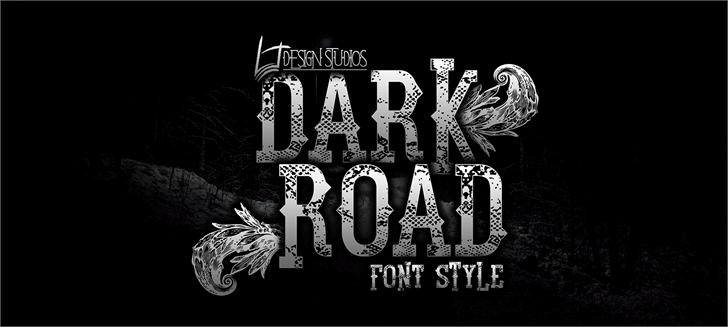
Dark Road Font – Fonte Grátis
Dark Road Font
A fonte ‘Dark Road Font’ é perfeita para criar design decorativos que se destacam na sua página web ou material impresso. Feita pelo designer Hamilton, essa fonte oferece linhas finas e elegantes com um toque sombrio que a torna ideal para ambientes criativos e interessantes. Com o uso desse recurso gráfico único, você pode adicionar um tom de profundidade única aos seus designs digitais. A ‘Dark Road Font’ é perfeita para criação de logotipos memoráveis ou para incorporar em websites modernos. Para obter as letras, números e símbolos comerciais da fonte, visite o endereço http://ljdesignstudios.es.tl/Dark-Road.htm, ou entre em contato com o designer Hamilton através do email .